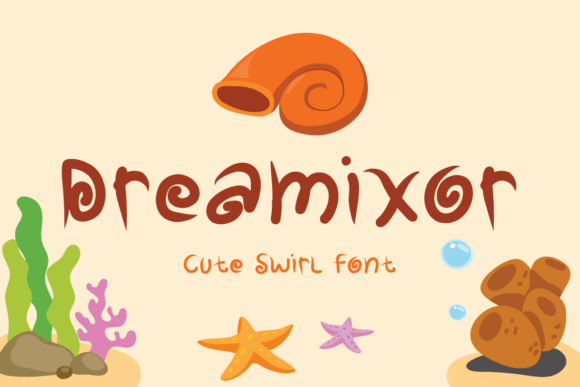
Dreamixor
Trouver les bons éléments de conception peut être un défi, mais Dreamixor propose une collection exceptionnelle qui rehausse instantanément votre travail.
Que vous créiez des produits POD (impression à la demande), des invitations de mariage ou des visuels pour les réseaux sociaux, Dreamixor est un choix idéal.